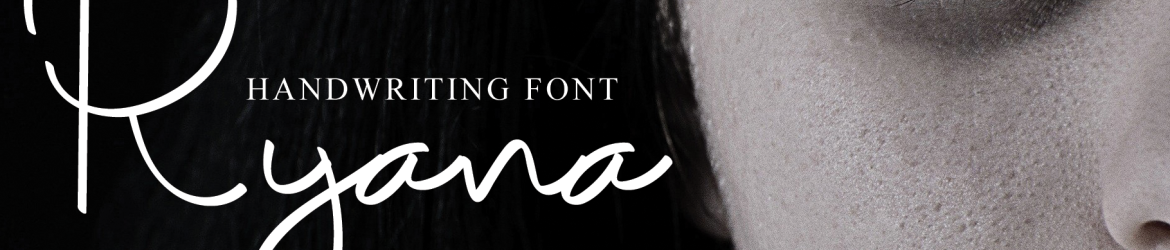
Ryana Font – Download Grátis
A Ryana Font é uma elegante caligrafia relaxada perfeita para quem deseja adicionar um toque autêntico a seus designs digitais. Se você busca uma fonte que seja tanto charmosa quanto prática, não há melhor escolha do que a Ryana. Esteve cuidadosamente elaborada para oferecer detalhes impecáveis e estilo moderno. Com sua versatilidade, é perfeita para qualquer projeto – seja um logo, um site pessoal ou até mesmo uma simples assinatura de texto. A Ryana não apenas complementa seu espaço visual, mas a torna ainda mais memorável. Este font é perfeito para aqueles que valorizam tanto qualidade quanto criatividade na sua arquitetura tipográfica.